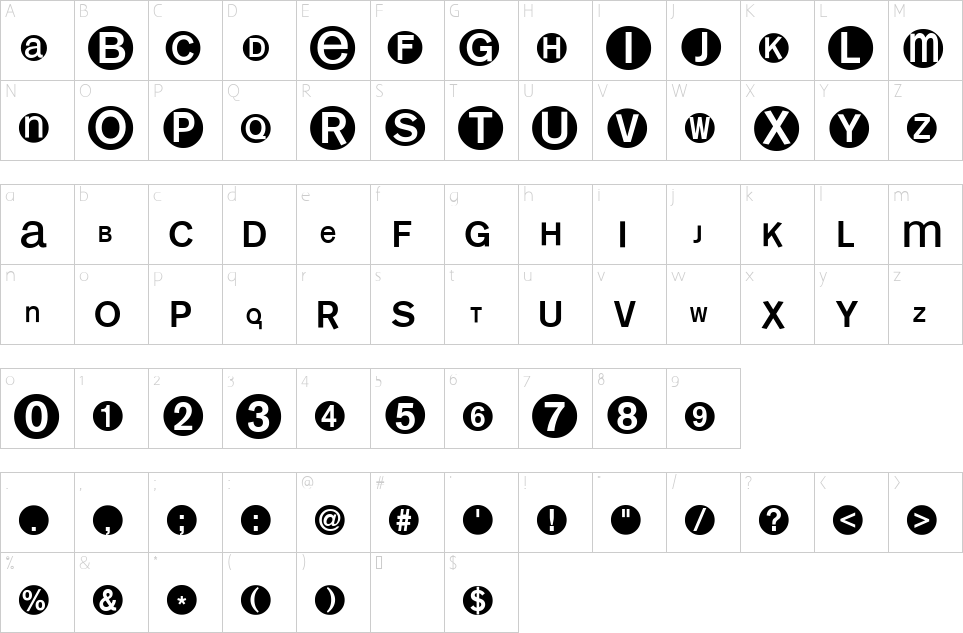
Baixe a fonte Mono Alphabet Multi Sized para Windows e Mac. Esta fonte foi projetada por Manfred Klein e já foi baixada 7.933 vezes. Mono Alphabet Multi Sized é uma fonte robusta e versátil, ideal para textos de tamanho variado em projetos digitais. Seja para o seu blog, site ou qualquer projeto gráfico que exige legibilidade e profissionalismo, esta fonte é uma ótima opção. Com seu design clean e moderno, a Mono Alphabet Multi Sized certamente complementará seu trabalho de uma maneira única e assertiva. Descubra agora mesmo a versatilidade e o poder desta fonte gratuita.